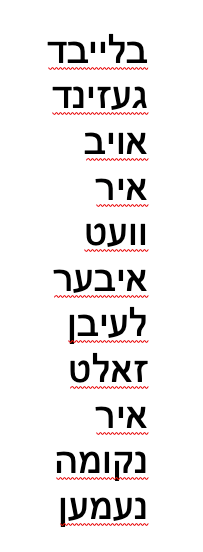
Kann jemand hebräisch?
kann jemand von euch hebräisch und mir sagen, ob dieser Screenshot aus Word korrekt gesetzt ist, also die Schriftrichtung richtig ist? Und falls ja, mir das in Indesign oder Illustrator Middle East kurz in der Arial Hebrew Regular und Bold setzen könnte?
@JulieParadisevielleicht?
Kann es sein, dass das Jiddisch ist, nicht Hebräisch?
װעט איר אויב געזינד בלייבד נקומה איר זאלט לעיבן איבער נעמען
"vet ir aoyb gezind bleybd nkumh ir zalt leibn iber nemen"
Wenn Sie sich weiterhin rächen, übernehmen Sie Ihr Leben
Sagt jedenfalls GoogleTranslate, weil ich aus dem "Hebräischen" keinen Sinn entnehmen konnte. :-o
Habe ich auch schon bemerkt, weißt du ob jiddisch von links nach rechts geschrieben wird? Ich wundere mich, weil Google übersetzer da etwas ausspuckt …
Ich habe ein neues Dokument bekommen, dass ich nehmen soll und da steigt Google Übersetzer aus … scheint zumindest weniger Sinn zu ergeben
Es kommt ja in verschiedenen Sprachen und Dialekten vor, dass Sprachsysteme vermischt und Glyphen einer anderen Sprache verwendet, dabei bleibt aber die Schreibrichtung der Schrift die gleiche wie sonst mit dieser Schrift auch, etwa bei aramäischen Dialekten: Werden sie mit arabischen Buchstaben geschrieben, dann von rechts nach links, mit lateinischen von links nach rechts.
Für das Jiddische kenne ich es auch nur (aus sehr wenigen Kursen vor bald 15 Jahren, "Ghetto-Literatur" usw.), dass sie mit hebräischen Buchstaben von rechts nach links gehen, lateinisch von links nach rechts.
In der Reihenfolge oben macht das aber durchaus was her:
בלייבד געזינד אויב איר װעט איבער לעיבן זאלט איר נקומה נעמען <--
--> bleybd gezind aoyb ir vet iber leibn zalt ir nkumh nemen
Bleib in Sicherheit, wenn du überlebst, wirst du Rache nehmen
PS: Von der ganzen Wortanlage her klingt nur
נקומה
nk(u/o)m-h
semitisch/hebräisch, nakamah ist 'Rache', der Rest ist lautgetreu wiedergegeben.
Herzlichen Dank liebe Julie!
Habe mich heute gefühlt, als hätte ich mich in Japan verlaufen ;-)
Eben ging meine RZ zur Freigabe, nachdem ich den Text in Indesign Buchstabe für Buchstabe umgesetzt habe … bin gespannt, aber die rein visuelle Kontrolle hat immerhin mit dem Word-Dokument überein gestimmt. Ich mache Feierabend und werde morgen noch ein bisschen NAKAM! üben … Wochenendarbeit …